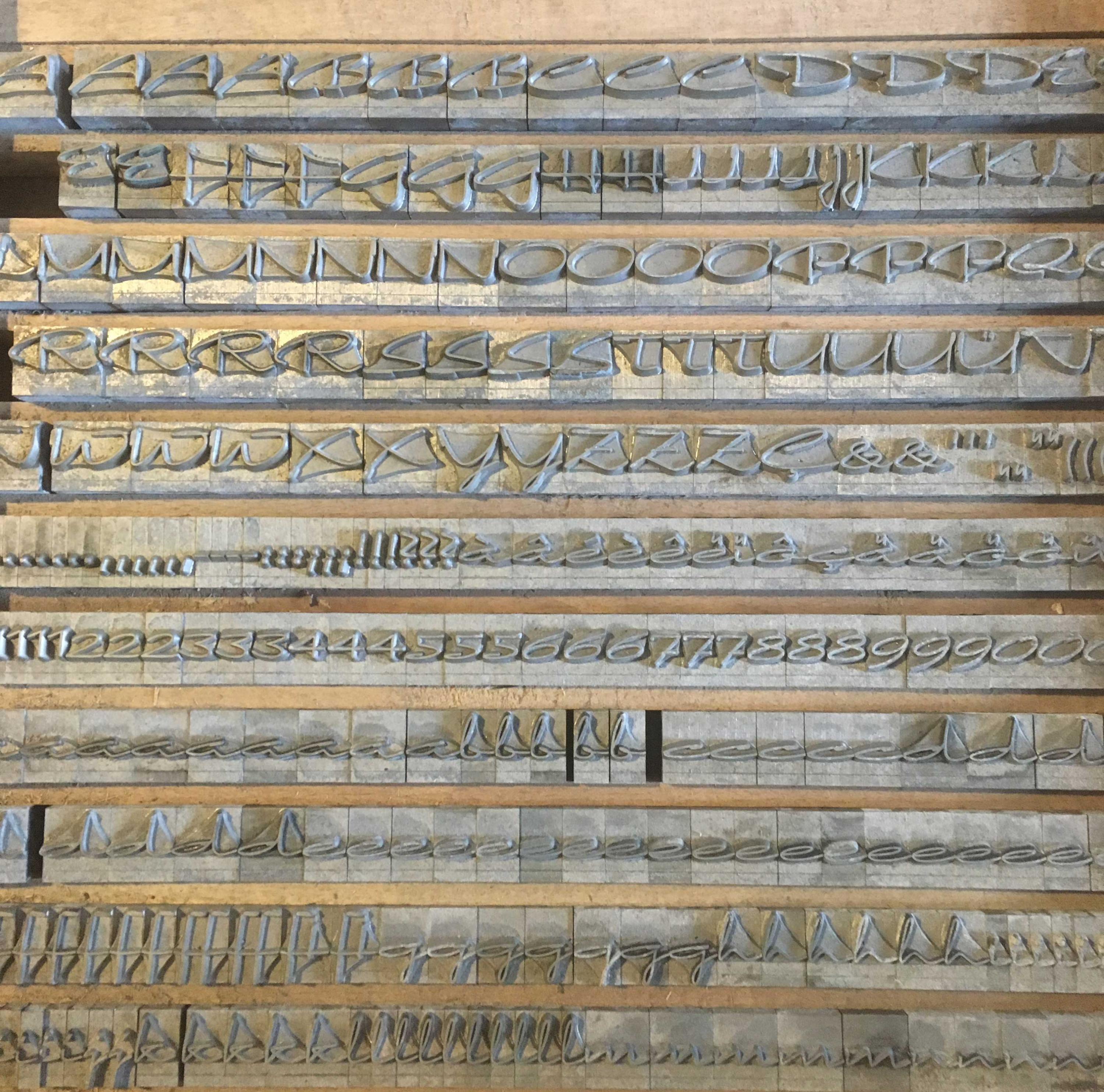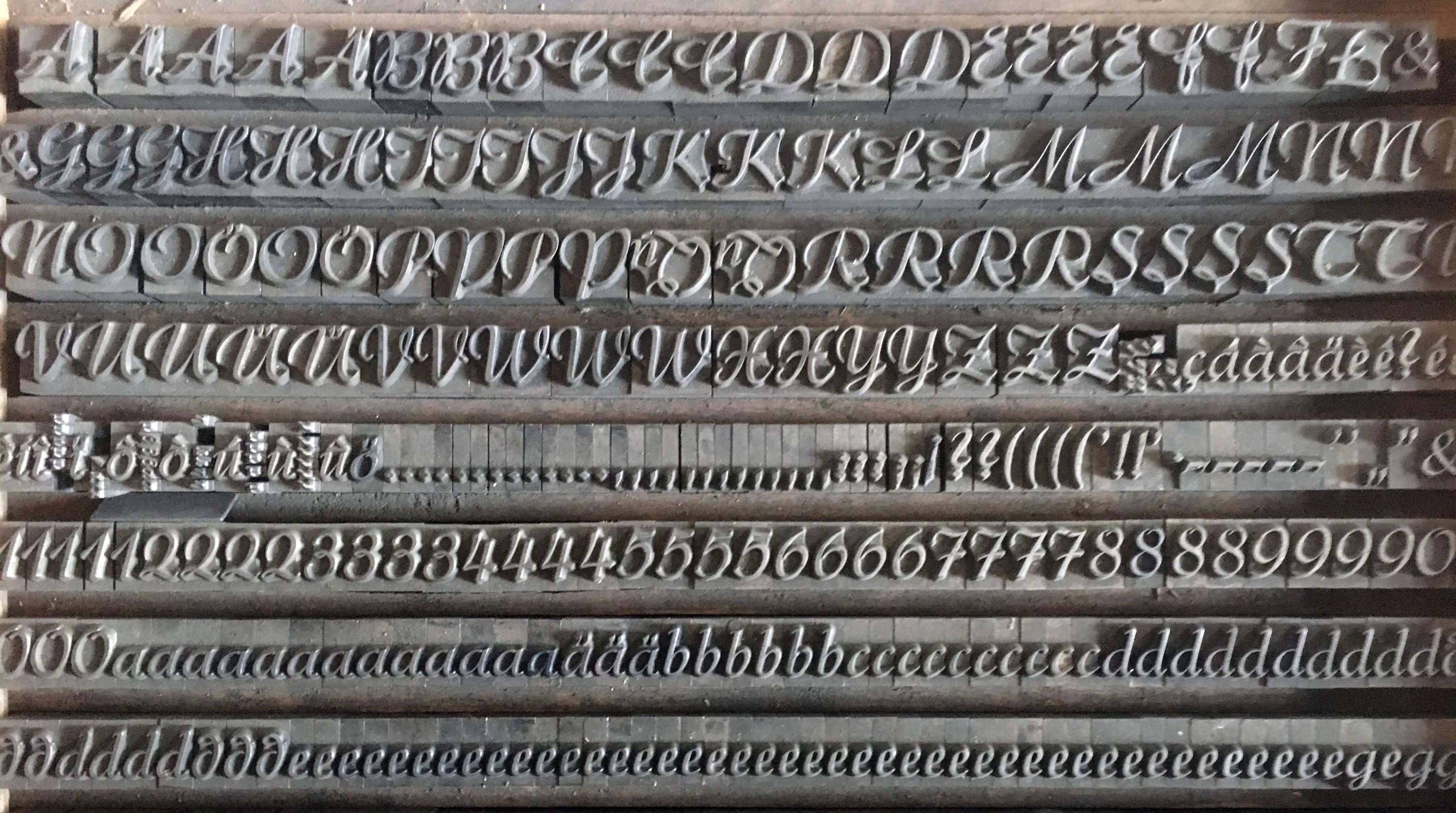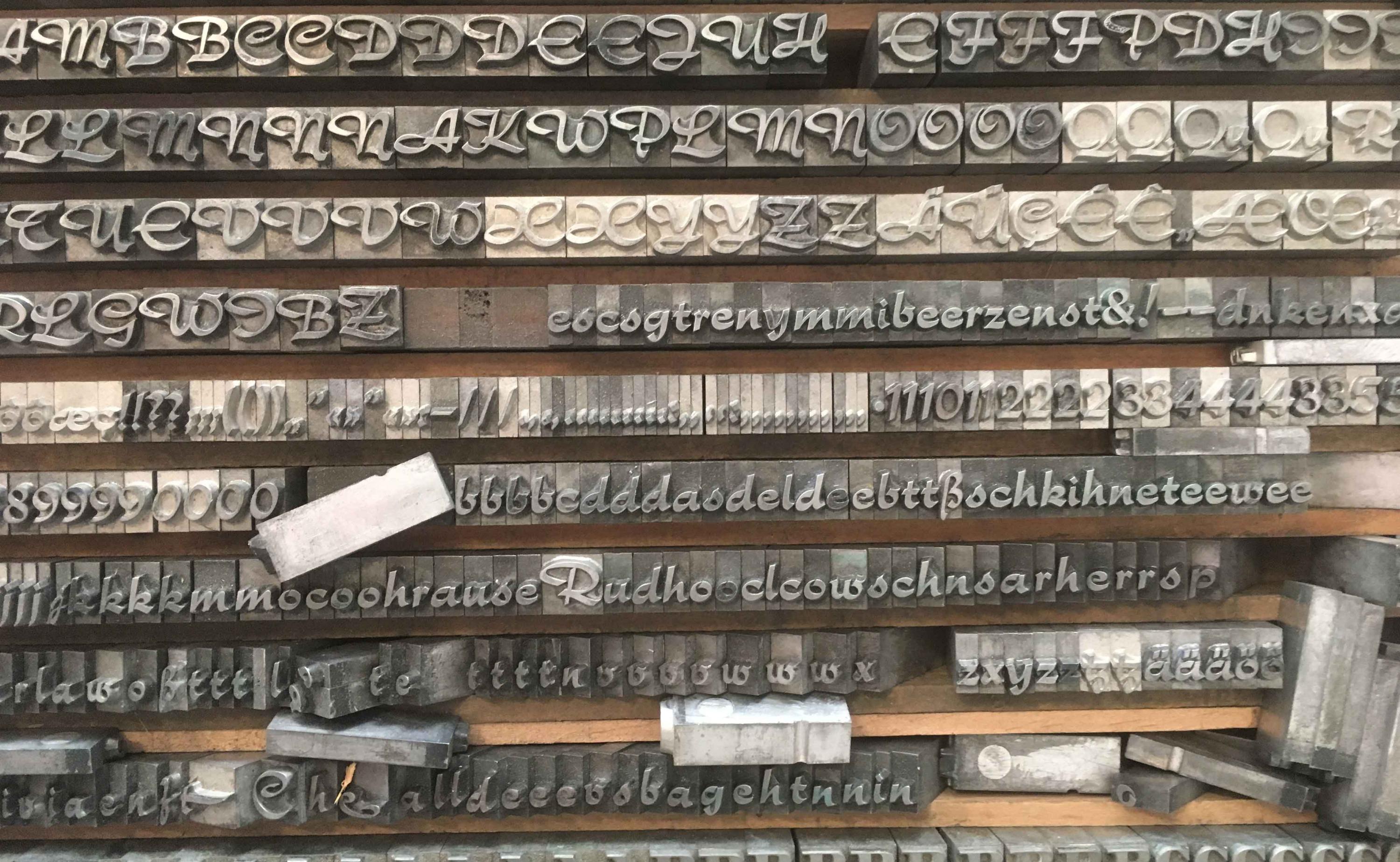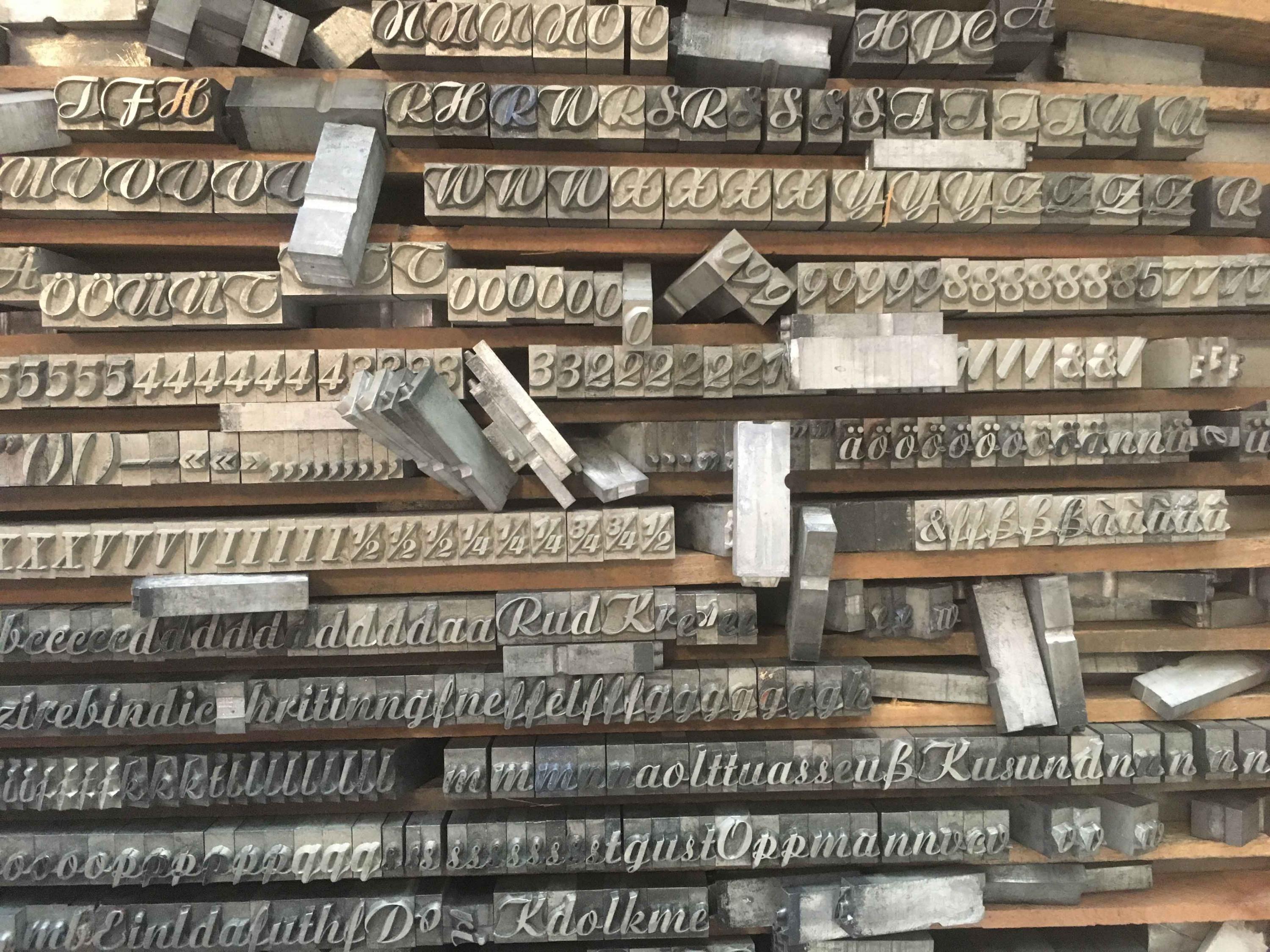
Unbekannte Bleischreibschriften
Gelöst von Martin Z. Schröder
Sehe eben, dass die „Charme“ in einer leicht fetteren Version unter dem Namen „Slogan“ 1958 ebenfalls bei Ludwig & Mayer gegossen wurde.
Ich kann mich persönlich aus meiner Bleisatzzeit nur an die „Charme“ erinnern.
Nummer 1 heute:
oder
Minuet, an informal script with crossover deco elements giving it an unmistakable 1940s flavor, is a revival and expansion of the Rondo family, the last typeface drawn by Stefan Schlesinger before his death.
This family was initially supposed to be a typeface based on the strong, flowing script Schlesinger liked to use in the ads he designed, particularly the ones he did for Van Houten’s cocoa products. But for technical reasons the Lettergieterij Amsterdam mandated the face to be made from unattached letters, rather than the original connected script.
Schlesinger and Dooijes finished the lowercase and the first drawings of the uppercase just before Schlesinger was sent to a prison camp in 1942. Dooijes completed the design on his own, and drew the bold according to Schlesigner’s instructions. The typeface family was finished in February of 1944, and Schlesinger was killed in October of that same year. Though he did see and approve the final proofs, he never actually saw his letters in use. It took almost four more years for the Lettergieterij Amsterdam to produce the fonts. The typeface was officially announced in November of 1948, and immediately became a bestseller. By 1966, according to a memo from the foundry, the typeface had become “almost too popular”.
This digital version of Schlesigner’s and Dooijes’s work greatly expands on the metal fonts. Both weights include a complete set of lowercase alternates — based on Schlesinger’s own drawings, as well as alternative variations for some of the capitals, a few ligatures, and extended language support covering Western, Eastern and Central European languages, plus Baltic, Celtic/Welsh, Esperanto, Maltese and Turkish.